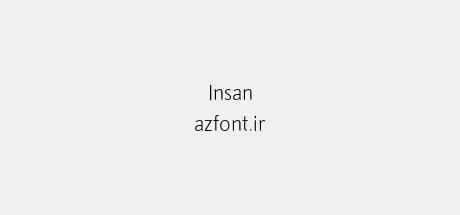
Insan
فونت زیبای رایگان Insan
قلم زیبای Insan Thin Regular از سری قلم های بسیار زیبا برای تایپوگرافی و لوگو تایپ می باشد.این قلم در وزن Thin و توسط Ihsan Al-Hammouri طراحی و منتشر شده است.